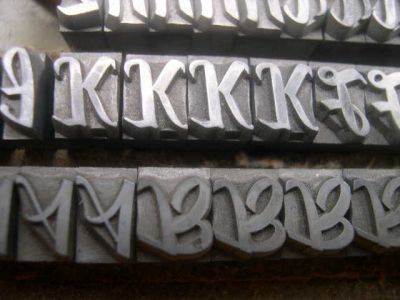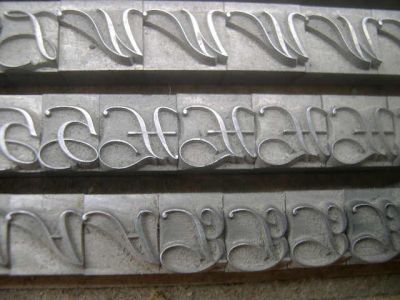
Heinrich sähe es als lösbare Aufgabe, beliebige 100 Versionen des Gemeinen a zu identifizieren. Mike Yanega zeigt uns allen auf Typophile, wo der Hammer hängt und identifiziert (fast) jede unbekannte Schrift.
Zeigt mir, daß Ihr das auch könnt.
Welche Schriften sind das?
Nein, ich weiß selbst auch nicht, um welche Schriften es sich hier handelt. Habe mich aber auch noch nicht näher damit beschäftigen können. Vermutlich stammen sie aus den 1920er Jahren, zumindest waren alle Schriften in diesem Satzschrank aus dieser Zeit.
Kurze Zwischenfrage,
könnte die unten abgebildete die »Holla« von Rudolf Koch sein?
(1932/Klingspor)
Nein, die ist irgendwie rauher?
Ich sage Euch, was ich nach nur flüchtigem Schauen vermute.
Die "üblichen" Quellen, also Seemann von 1926, Georg Kandler etc. habe ich durchgeschaut und nichts gefunden. Das weist darauf hin, daß...
... die Schriften nach 1926 herausgegeben wurden, aber mit ziemlicher Sicherheit vor dem Zweiten Weltkrieg. Die Anmutung der Schriften spricht dafür, der Zustand der Lettern und auch der Umgebung. Alle Lettern in dem Schrank waren aus dieser Zeit, alle Setzkasten-Schilder sind im selben Rutsch hergestellt worden.
... reines Spekulation: Es könnte sich um Schriften der Schriftguß A.-G. handeln. Der Schrank könnte aus dem Osten stammen (auch, wenn ich selbst ihn hier im Westen von einem alten Buchbinder bekam). Das würde auch erklären, warum ich die Schrift in der Schnelldiagnose nicht finde, denn ich habe keine Hauptprobe der Schriftguß.
Wie gesagt, die üblichen Vergleiche habe ich schon durch.
Da ist nichts bei.
Es ist nicht eilig. Ich kann den Schrank erst verkaufen, wenn die Schubladen leer sind. Leeren kann ich sie erst, wenn ich die Schriften heraushole. Herausholen kann ich sie erst, wenn ich weiß, welche Schriften es sind :twisted: Also laßt Euch ruhig Zeit. Meine Kinder hungern halt solange noch weiter...
georg ich bin mit blei nicht großgeworden, um das rauszubekommmen muss man sich zeit nehmen, das muss man wiederum wollen.
das wird schon einer schaffen.
Heinrich,
das war, bitte, nur ein Witz von mir.
Ich weiß das doch.
Begleitmusik: »Wette verloren!«
Voll abgeschmiert! Arno Drescher stimmt wohl auch nicht.
Tja, man muss auch mal verlieren können.
Behalt Dein Syndrom ruhig und such weiter, bitte.
Ansonsten schaue ich ab nächsten Dienstag ebenfalls.
Und werde natürlich berichten, falls hier nicht noch jemand anderen die Erleuchtung packt.
Für „bleiungewöhne“ Schriftleute ist es wohl einfacher die gespiegelten Bilder zu sehen; ich glaube dann ist es leichter, die Schriften zu erkennen.
Hoppla Georg
Offensichtlich hast Du uns hier ein ziemliches Stück Arbeit platziert, mit Deinen beiden Typen. Ich meinte anfangs, beide einfach so aus dem Ärmel schütteln zu können ... Snell Roundhand und Hauser Script. Glücklicherweise hab' ich das aber nicht laut gesagt, denn beide sind daneben. Tja, ist ja auch schon lange her, meine Bleizeit.
Aber etwas ganz anderes hab' ich immerhin gefunden (nehme jedoch an, dass Du die selbstverständlich und sowieso schon kennst):
Pater Meinrad hat eine Krause-Fraktur und ich weiß das nicht?
Unglaublich. Was für ein Sch...-Anfang für den Tag :evil:
Aber danke für den Hinweis.
Ich weiß tatsächlich (noch) nichts von dieser Schrift.
Vermutlich wird mir nichts anderes übrig bleiben, als zunächst einen kompletten Zeichensatz abzusetzen, anzudrucken und als "Typus Incognitus" in die Schriftensammlung aufzunehmen. Dann wird sich vielleicht früher oder später ein Besucher meiner Webseite melden und mir die Lösung mitteilen. Anders geht es nicht. Hans Reichardt mag ich nicht mehr fragen.
ist es möglich das es eine amerikanische schrift ist?
Nein, das ist nicht möglich.
Anglo-amerikanischer Bleisatz hat eine andere Schrifthöhe.
Das sind deutsche Schriften.
Ganz sicher aus Mitteldeutschland, mit hoher Wahrscheinlichkeit Schriftguß-Schriften.
Ich werde heute Abend mal die Schriften bei Typophile einstellen und Mike Yanega fragen. Der hat eine Schriftguß-Hauptprobe.
Dennoch danke für die versuchte Hilfe.
Ja, genau.
Und ich unterstelle, daß Du genau weißt, was ich meine.
Ich kann so überzeugend eine Schrift hier falsch klassifizieren, daß manche nie und einige erst nach Stunden darauf kommen.
Einfach klaaatsch, auf'n Tisch damit.
Die Holla muß ich andrucken und dann verkaufen.
Aber wenn ich sie angedruckt habe, schenke ich Dir die ausgebundene Satzform, wenn Du magst. Die Schrift ist bis dahin eh längst verkauft.
Damit kannst Du dann beim nächsten Mal den Haussegen ausgleichen. Die Form wiegt bestimmt zwei Pfund oder so.